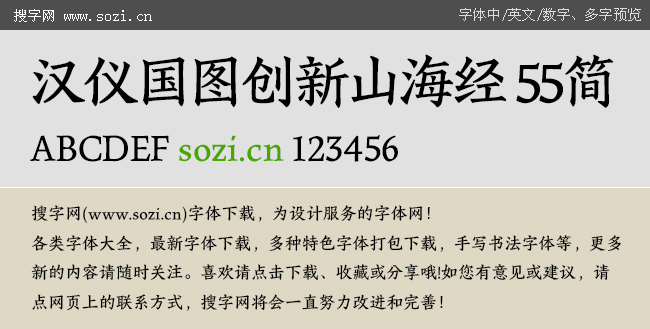
漢儀國圖創(chuàng)新山海經(jīng) 55簡
搜字網(wǎng)給大家提供一款漢儀國圖創(chuàng)新山海經(jīng) 55簡中文字體下載,漢儀國圖創(chuàng)新山海經(jīng)字體是一款充滿古典韻味的字體,其設(shè)計靈感來源于中國古代的山海經(jīng)。這款字體的特點是筆畫線條流暢,字形簡潔大方,有一種古樸而莊重的感覺。適用于畫冊設(shè)計、海報設(shè)計、包裝設(shè)計等場合使用。(本字體為個人非商用版,如需要商用請聯(lián)系漢儀公司購買版權(quán))
• 風格類別: 楷體